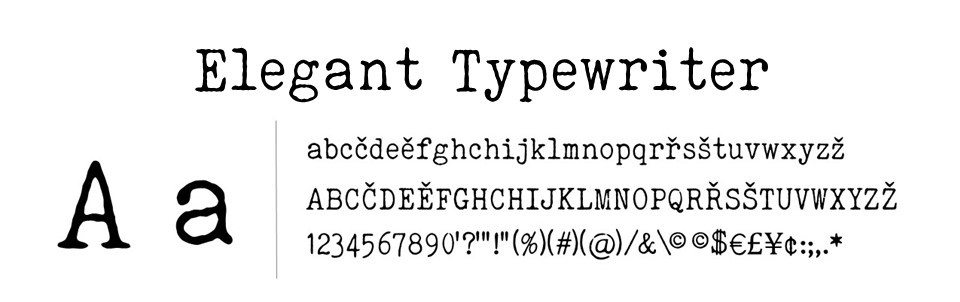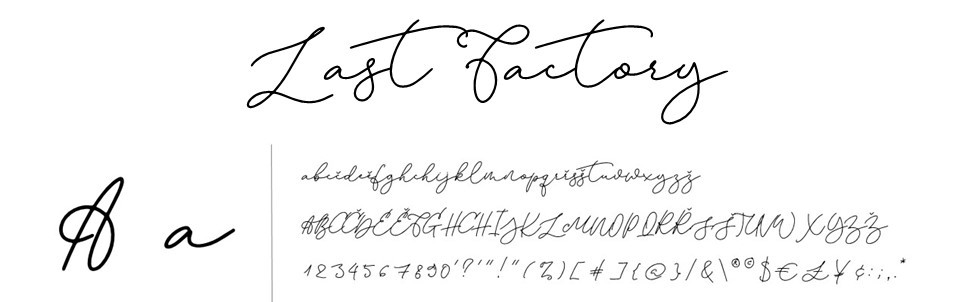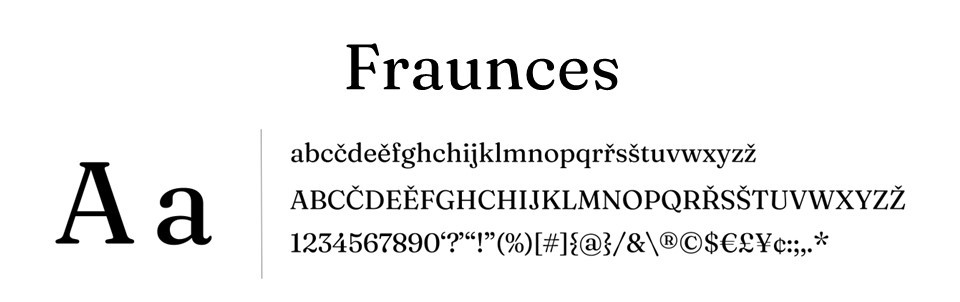
I když působíte velmi žensky, máte sílu a energii muže. Nejdůležitější pro vás je autenticita, být svá, nezapadnout do šedého davu a průměru. Máte odvahu vystoupit z řady, dělat nečekaná rozhodnutí a dokonce je často i měnit. No a co. Změna je život.
Proměnlivost je vaší součástí a nedočkáme se od vás stereotypů nebo zaběhaných zvyků. Nejvíce se bojíte přízemnosti, nudného stereotypu a bezmyšlenkovitého následování pravidel a tradic.
Podle toho, jestli jste spíš introvert nebo extrovert, se můžete najít v:
- Citlivkách, které mají silně vyvinutou intuici, cit pro velmi jemné nuance života. Vaše rebelství není o extravaganci, ani ho netoužíte ukazovat celému světu, často je spíš v postojích, názorech, které jdou proti proudu anebo v detailech, špercích, doplňcích. Mnoho z nich je vaše srdcovka a poznávací znamení. Nesnášíte "takhle to má být, lidi to tak chtějí", i za cenu sebezničení uděláte raději opak.
VAŠE HODNOTY: intuice, opravdovost, upřímnost, cit pro detail. - Hvězdách, pro které je noční můra zapadnout do šedi a nudy. Velmi často silně extrovertní, máte potřebu být vidět. Máte sebevědomí a nebojíte se vyčnívat a být odlišní od všeho a od všech. Milujete změnu, rychlost, aktivitu. Nemíváte mnoho oblíbených kousků, které byste si vzali na sebe vícekrát, změna je život a vy ho chcete žít. Nemáte rádi usedlost, ledové královny, něžnou romantiku, zdrženlivost a opatrný přístup.
VAŠE HODNOTY: sebevědomí, energie, změna, odvaha - Rebelech, pro které je na prvním místě potřeba být naplno sám sebou, bez zbytečných zabředávání do emocí a hloubání. Jste jací jste a rádi to narovinu ukážete. A tak trošku vás baví i provokovat a jít cíleně proti proudu. Také nesnášíte „takhle to má být“..., stejně jako Citlivky, ale u vás nemůže být řeč o sebezničení, když uděláte pravý opak. Vy si rebelii naopak užíváte.
VAŠE HODNOTY: nezávislost, pragmatičnost, akce.
U všech typů převládá na první dobrou mužský princip. Je v podvědomí nahoře, zodpovědný za první reakce, které jsou racionální nebo sebevědomé. Pokud se cítíte bezpečně, dostává se ke slovu i ženský princip, který je schovaný uvnitř a je stejně silný, jako ten mužský navenek. Velmi silné emoce, u kterých si nejste jisti, jestli je pustit ven.
Často působíte navenek jinak, než se cítíte, máte velmi bohatý vnitřní svět. Uvnitř jste emoční, spontánní, citliví - ale navenek často přejímáte mužský racionální nebo sebevědomý postoj. Oceňujete u sebe i u druhých osobitost, kterou tvoří detaily, kterých by si ostatní ani nevšimli.
Vaše přednosti:
- autenticita
- originalita
- odvaha
- smysl pro detail
- smysl pro efekt
- intuice
- nápady, kreativita
- proměnlivost
1. Citlivka
2. Hvězda
3. Rebel
FONTY VÁM PŘITÁHNOU NEBO ODRADÍ KLIENTY
Výběrem písma na web, předáváte jasné a konkrétní informace o vaší značce podvědomí klienta.
Můžete si cíleně vybrat takové, kterými přitáhnete ideálního zákazníka a odradíte potížisty.
Fonty na nás působí jak svým vzhledem, tak díky asociacím, které v nás probouzí. Sklon písma, řád, chaos, křivky, mezery, poměry výšky a šířky písmen, to vše hraje roli a okamžitě ovlivňuje naše vnímání. A vzbudí EMOCE. A emoce hrají ve světě marketingu a podnikání klíčovou roli. Díky nim dokážete oslovit konkrétní cílovou skupinu, přitáhnout pozornost tam, kde potřebujete (třeba na to správné tlačítko) anebo vyhrát prezidentské volby.
Zkrátka a dobře, v online i offline světě není možné oddělit formu a obsah textu, a z marketingového hlediska dokáže právě font sám o sobě zásadně ovlivnit to, jak vnímáme obsah sdělení. Je v něm důvěra a spolehlivost, nebo lehkost a nadsázka?